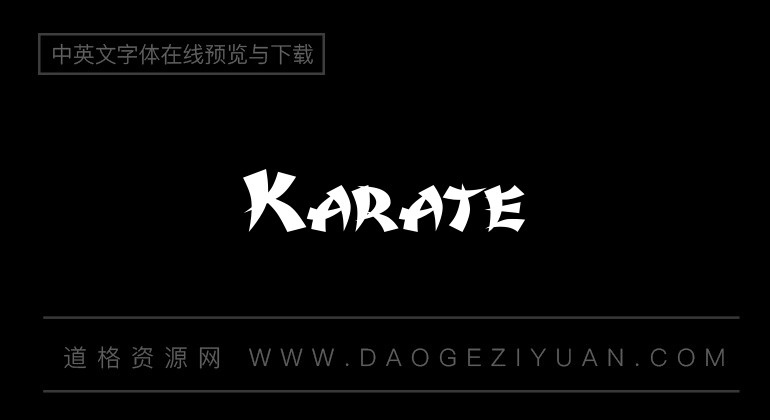
Karate
Karate 是一款中国风格的字体,由著名字体设计师黄晓鹏设计。它有着中国传统结构的繁复线条,可以在现代设计中起到突出的作用。Karate 字体的特点是细节丰富,线条流畅,曲线细腻,笔画精致,强调结构的秩序和美感,表达出传统中国文化的特色。它可以用于商标、标志、海报、书籍、网站等设计中,能够给设计师带来更多的创意灵感。
Karate是一款非常不错的手写艺术字体,具有很好的视觉感,适合于文化类的宣传设计、商业类品牌的广告和产品包装设计以及个性化文字排版等较多场景。